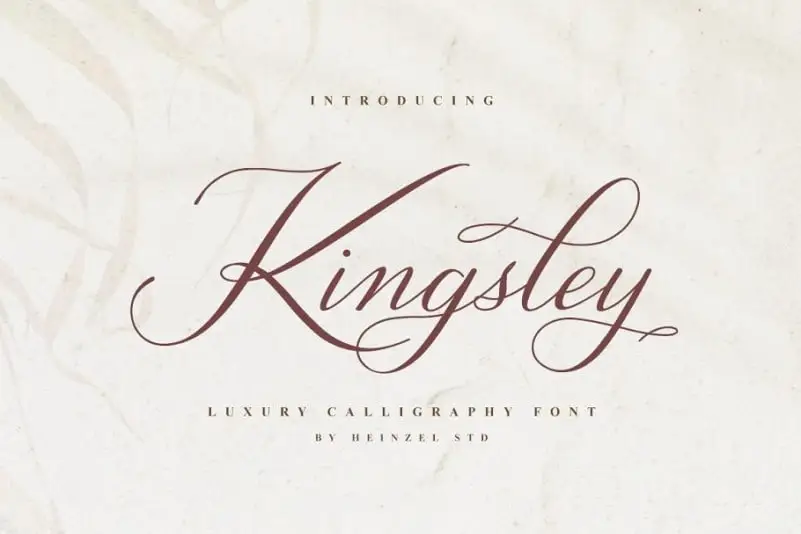
A Kingsley Calligraphy Font é uma escolha perfeita para projetistas que buscam uma mistura única e elegante de estilo clássico com atualidade. Esta fonte tem um ar descontraído, agradando tanto os designers tradicionais quanto aqueles buscando algo mais moderno. Os parágrafos são fluidos e bem estilizados, enquanto as alternativas gráficas fornecem uma versatilidade única. A Kingsley também inclui todos os caracteres maiúsculos e minúsculos, símbolos multilingues, números e pontuação, garantindo que você possa explorar a totalidade do seu potencial criativo. Ouvido atento à sua precisão, os desenhos são detalhados, as linhas sutilmente suaves e os caracteres gráficos impressionantes. A Kingsley mantém seus influências clássicas em graça, ao mesmo tempo que parece fresco e atual. Para quem busca algo diferente do estável dos padrões tradicionais, esta fonte é uma excelente escolha. Para projetos que valorizam o cuidado na formação da letra e a precisão na aplicação de tipografia, a Kingsley é certamente um ótimo investimento. Suas alternativas gráficas podem fazer sua obra mais chamativa e única ao mesmo tempo em que manter seu estilo clássico. Fique encantado com esta fonte e transforme seus projetos em verdadeiros estalajadores!